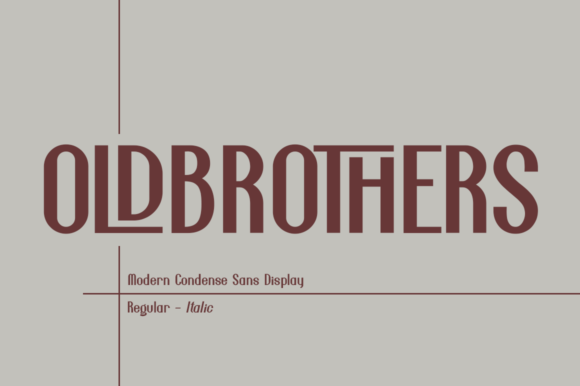
Creativefabrica Oldbrothers Font
[Creativefabrica] Oldbrothers Font
Old Brothers - это простое начертание полужирного шрифта.
Мастерски разработанный, чтобы стать настоящим фаворитом, этот шрифт способен поднять каждую вашу творческую идею на самый высокий уровень!